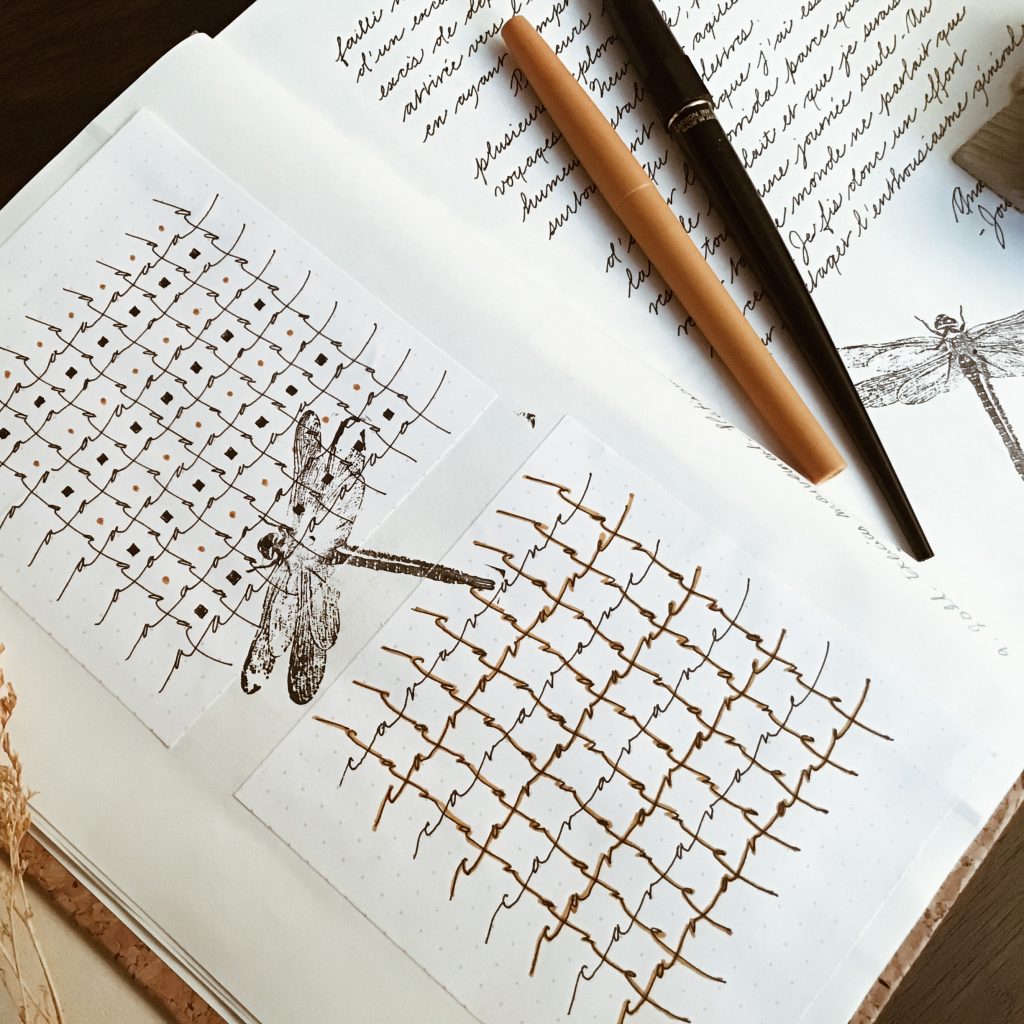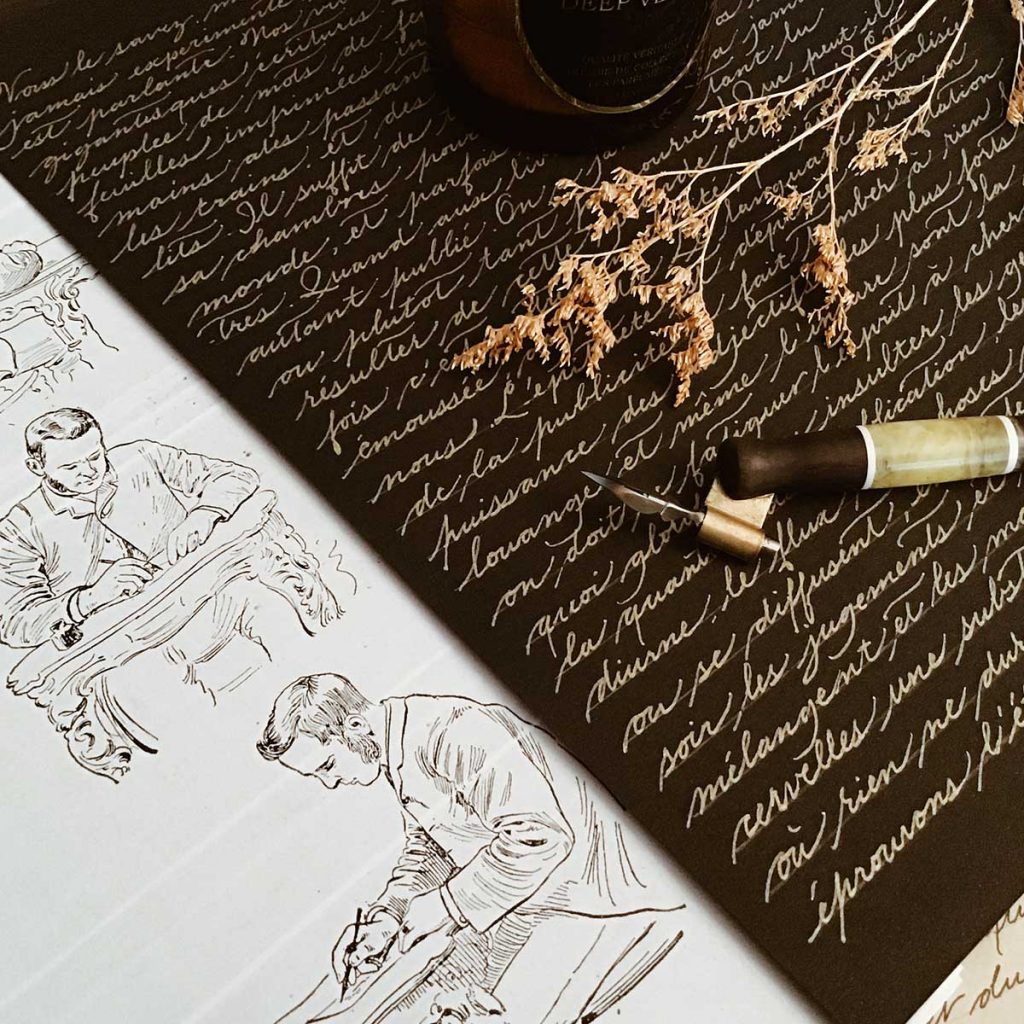
Le printemps et l’été n’ont pas été très productifs côté calligraphie. J’avoue même que je n’ai pas touché une plume ou un pinceau pendant plusieurs semaines. Mais l’inspiration et l’envie re-pointent leur nez avec le début de l’automne, une saison que j’affectionne beaucoup car elle marque le retour au cocooning, aux belles couleurs chaudes et envoutantes. On passe un peu plus de temps à l’intérieur, et on ressort aussi plumes, papiers et encres.
L’envie du moment : apprendre la Spencerian
Cela fait longtemps que ça me travaille et je n’avais jamais trouvé le temps, ni la bonne méthode peut-être. J’ai finalement trouvé des ressources, notamment sur le blog Penna Volans, le site génial de Sibylle van Zuylen qui recense une bibliographie gigantesque sur les écritures du XIXeme siècle (entre autres, allez faire un tour, c’est une mine d’or !).
Bref, j’ai téléchargé la Méthode Palmer, regardé quelques vidéos et j’essaie de travailler un peu tous les jours.
Je consigne mes progrès dans un carnet, ceci afin d’éviter le problème habituel des brouillons qui s’entassent et qui ne servent plus à rien. Je garde les meilleurs morceaux, un coup de ciseau, un peu de collage et hop je jette le reste. Mine de rien ça allège le bureau et l’esprit !
Pour le moment je me concentre sur l’écriture basique, sans majuscules complexes, sans arabesques. J’écris au roller ou avec un stylo plume classique la plupart du temps. L’objectif est de capter le rythme particulier de cette écriture, qui doit être exécutée, en outre, avec une extrême régularité.
J’avais commencé à la plume, mais j’ai vite renoncé pour travailler les bases plus simplement. Je ferais peut-être un article un peu plus complet sur la Spencerian quand j’aurais progressé.
Quelques essais à la plume coudée
Un tableau tout nouveau
J’ai toujours du mal à faire des compos dignes d’être encadrées. Néanmoins j’ai fait un tableau sympa reprenant des encrages de végétaux, un peu d’anglaises, quelques arabesques et ma foi, je l’ai encadré.